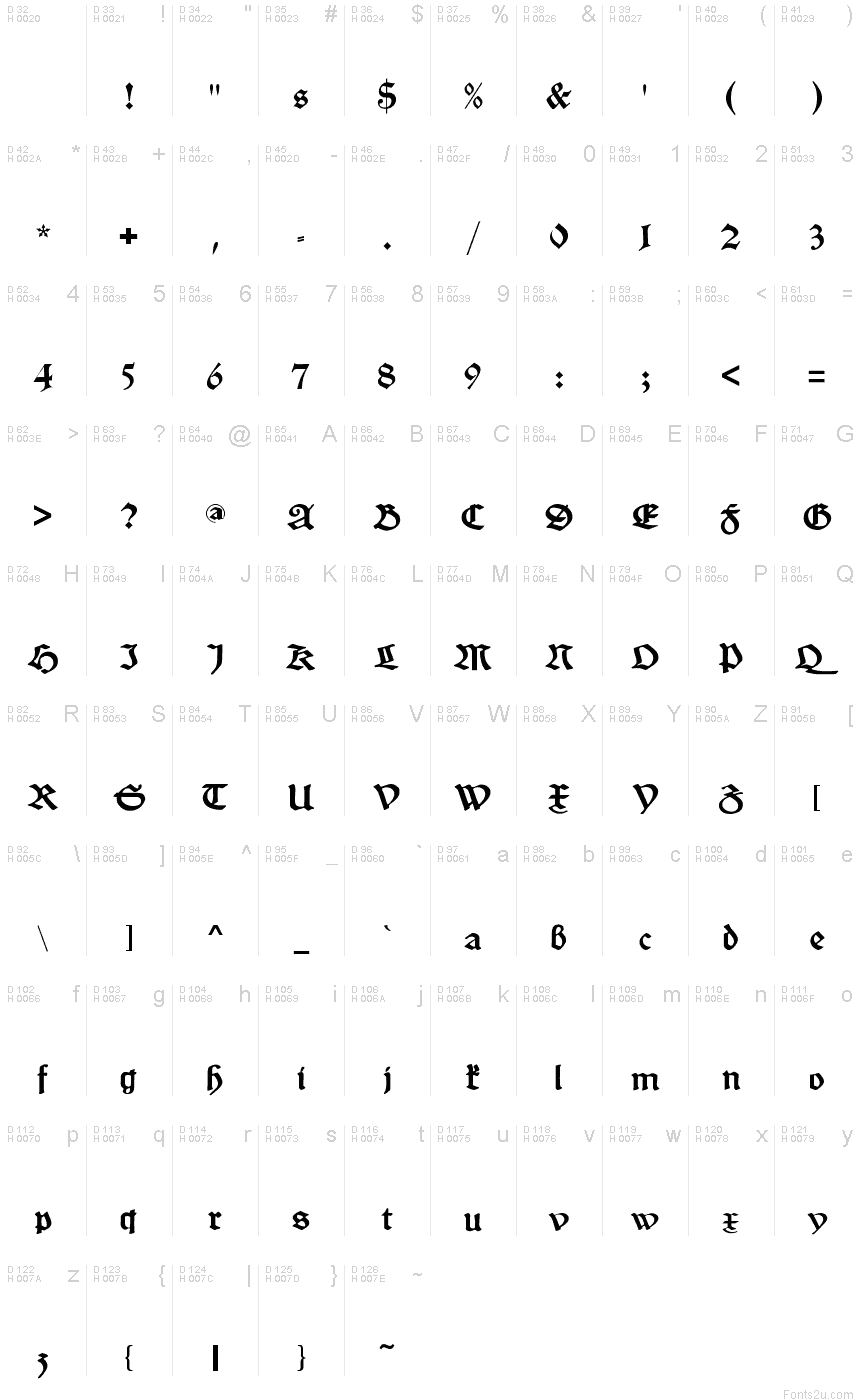
SchneidlerSchwabacher
Schneidler Schwabacher, wydana w 1913 roku przez Schelter + Giesecke i zdigitalizowana przez Manfreda Kleina oraz Petrę Heidorn, to darmowy krój pism gotyckich Schwabacher. Jej szerokie, zaokrąglone pociągnięcia łączą się z uciętymi końcami i żywymi, haczykowatymi ozdobami.
W wydawnictwach historycznych oferuje gęstą fakturę i dawny klimat kojarzący się z niemieckim pismem gotyckim, a jej dramatyczna sylwetka sprawdza się również na plakatach muzycznych i gadżetach. Na opakowaniach piwa czy w oznakowaniu festiwali liternictwo może stać się częścią ilustrowanego herbu, zamiast służyć jako neutralny tekst.
1913 bei Schelter + Giesecke. Digitized by Manfred Klein und Petra Heidorn.